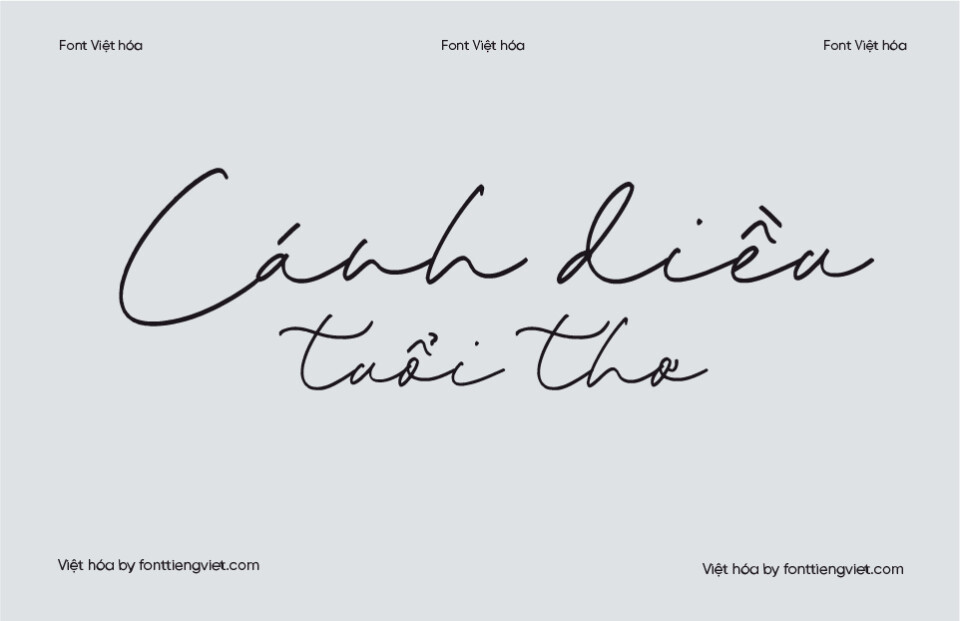
Giới thiệu về bộ Font Việt hóa 1FTV Eastin Hikary
Trong thế giới đồ họa hiện đại, việc lựa chọn Font Chữ phù hợp đóng vai trò then chốt để tạo nên bản sắc riêng cho tác phẩm. Font Việt hóa 1FTV Eastin Hikary là một bộ font mang phong cách hiện đại, thanh lịch nhưng không kém phần phá cách. Được thiết kế với những đường nét trau chuốt, bộ font này giúp các bạn học sinh và thầy cô dễ dàng ứng dụng vào việc làm báo tường, thiết kế slide bài giảng hoặc các dự án sáng tạo cá nhân một cách chuyên nghiệp nhất.
Đặc điểm nổi bật của font chữ này
Điểm mạnh của Font Việt hóa 1FTV Eastin Hikary chính là sự cân bằng giữa tính thẩm mỹ và khả năng đọc hiểu. Các ký tự được tối ưu hóa chuẩn bảng mã Unicode, đảm bảo không bị lỗi dấu tiếng Việt khi soạn thảo văn bản. Với bộ ký tự đa dạng, người dùng có thể linh hoạt sử dụng trong nhiều ngữ cảnh từ tiêu đề trang trọng đến các đoạn trích dẫn nghệ thuật, giúp nội dung truyền tải trở nên sống động và thu hút người xem hơn bao giờ hết.
Cách ứng dụng Font Việt hóa 1FTV Eastin Hikary hiệu quả
Để tận dụng tối đa vẻ đẹp của bộ font này, bạn nên kết hợp với các tông màu tối giản hoặc pastel nhẹ nhàng. Đối với các dự án trường học, hãy dùng font này cho các đề mục lớn để tạo điểm nhấn thị giác. Ngoài ra, việc điều chỉnh khoảng cách giữa các chữ cái (kerning) cũng giúp bố cục trở nên thoáng đãng và dễ nhìn hơn trên cả màn hình máy tính lẫn bản in giấy.